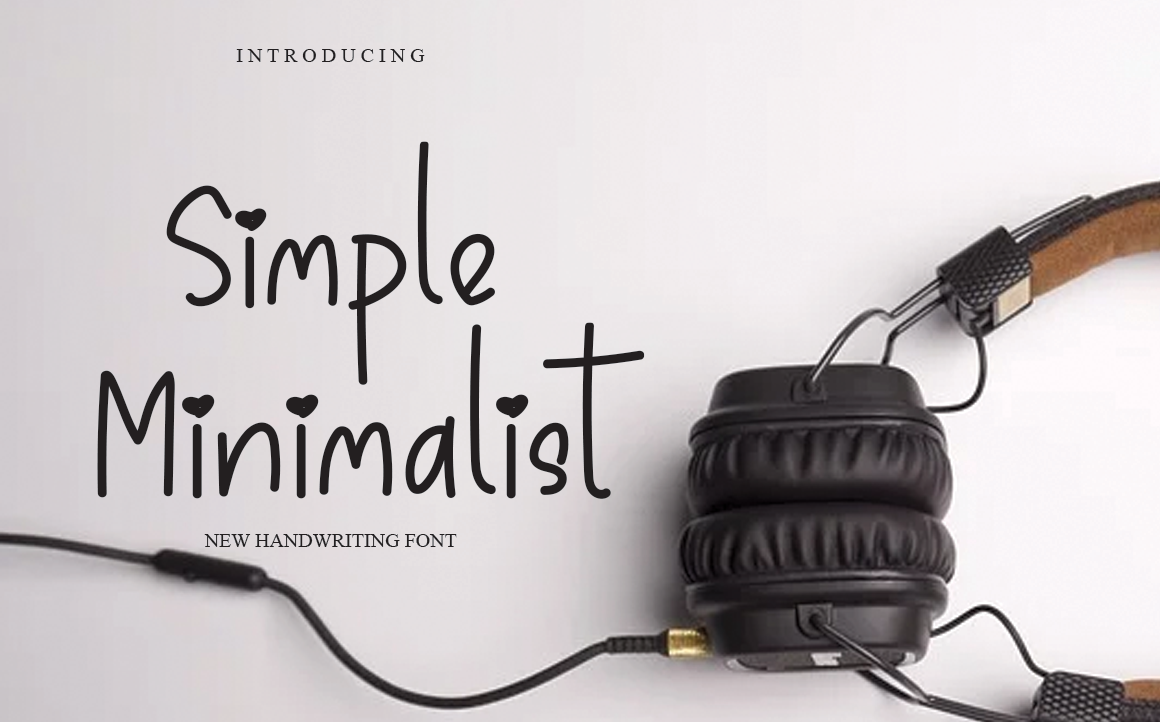
Simple Minimalist Font – Download Grátis
Esta é uma fonte escrita a mão única, divertida e amigável perfeita para quem procura algo diferente no seu design digital. Seja você que busque uma fonte adequada para um post do Instagram ou até mesmo uma tradição de caligrafia em projetos DIY, essa fonte transformará qualquer ideia criativa num verdadeiro trabalho de arte! Ela combina a simplicidade inigualável e o minimalismo com uma personalidade encantadora. Perfecta para dar um toque especial ao seu projeto visual, seja ele para redes sociais ou projetos pessoais onde você deseja manter as coisas simplesmente perfeitas. A fonte simplesmente brilha na web, em sites, emails e até mesmo em impressões de fotos, oferecendo um acabamento autêntico aos seus trabalhos digitais. Seja para criar design gráfico profissional ou para adicionar um toque pessoal a seu conteúdo online, essa fonte é o sonho dos designers.